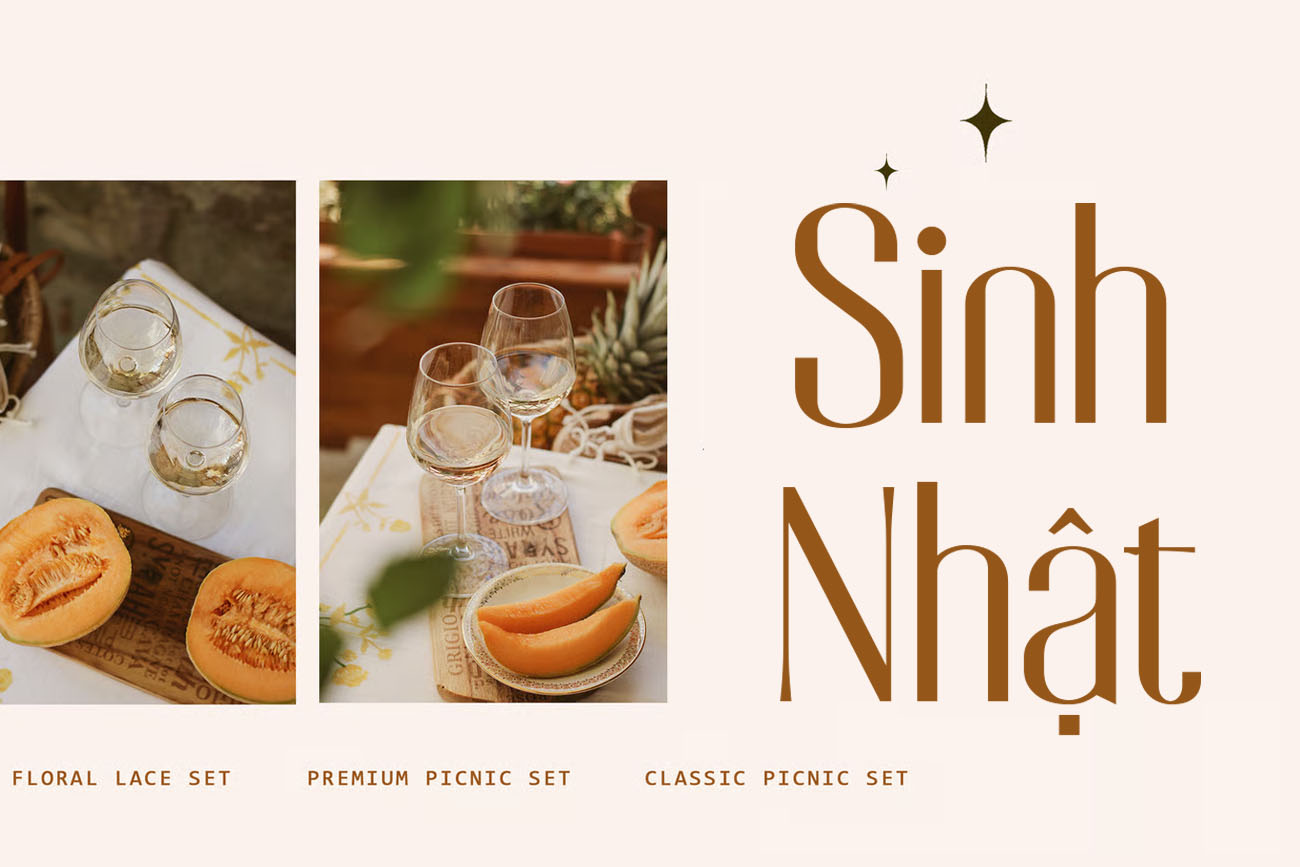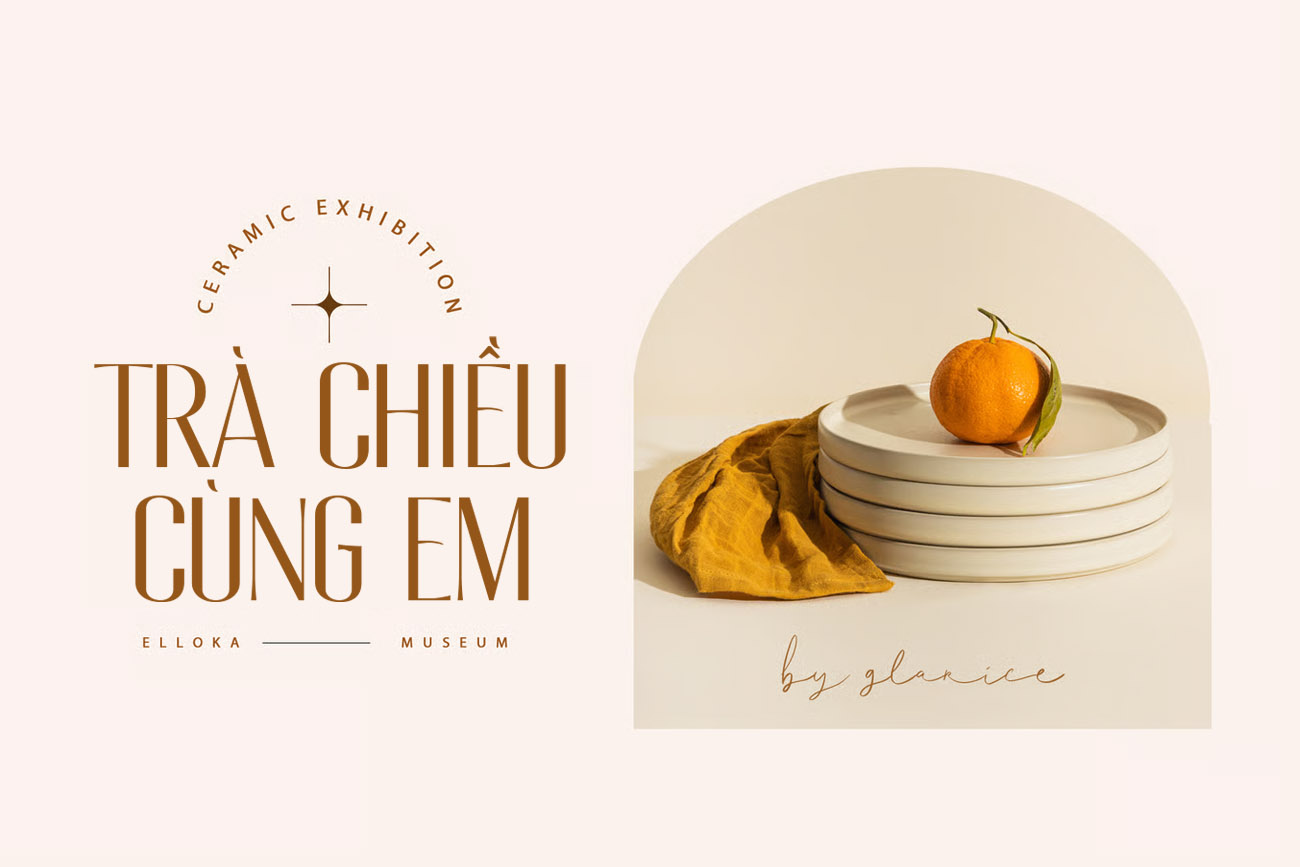
Font Chữ Việt Hóa Phong Cách Condensed Hiện Đại TH Belly & Park
Trong thế giới thiết kế đồ họa, việc tìm kiếm một font chữ hiện đại nhưng vẫn giữ được nét thanh lịch và sang trọng luôn là bài toán khó đối với các designer. Để đáp ứng nhu cầu này, hôm nay chúng tôi xin giới thiệu đến cộng đồng sáng tạo bộ phông chữ TH Belly & Park, một tác phẩm ấn tượng được Việt hóa hoàn chỉnh, sẵn sàng nâng tầm mọi dự án thiết kế của bạn.
Sự giao thoa tinh tế trong thiết kế gốc
Belly & Park, tác phẩm gốc của nhà thiết kế tài năng Yipianesia, là một bộ typeface thuộc dòng Sans Serif với phong cách Condensed (thu hẹp bề ngang). Ngay từ cái nhìn đầu tiên, bộ phông này đã chinh phục người xem bởi vẻ đẹp "Beauty Classic" – một sự kết hợp hoàn hảo giữa cấu trúc hình học hiện đại và những đường nét mềm mại, hoài cổ.
Điểm đặc biệt của Belly & Park nằm ở sự tương phản nhẹ nhàng giữa các nét, tạo nên cảm giác cao ráo, thanh thoát nhưng vô cùng vững chãi. Đây là lựa chọn lý tưởng cho những ai đang tìm kiếm sự tối giản nhưng không hề đơn điệu.
Phiên bản Việt hóa hoàn hảo từ Team TH
Hiểu được giá trị thẩm mỹ của bộ phông này cũng như nhu cầu sử dụng tiếng Việt trong các thiết kế chuyên nghiệp, Team TH đã tiến hành thực hiện phiên bản font chữ Việt hóa mang tên TH Belly & Park.
Không chỉ đơn thuần là thêm dấu, Team TH đã dành nhiều tâm huyết để tinh chỉnh lại kerning (khoảng cách giữa các ký tự) và vị trí của các dấu câu sao cho hài hòa nhất với cấu trúc Condensed đặc trưng của font gốc. Nhờ đó, các đoạn văn bản tiếng Việt khi hiển thị vẫn giữ được "linh hồn" và sự mượt mà vốn có của bản gốc, giúp các designer không còn lo lắng về lỗi hiển thị hay sự mất cân đối khi gõ tiếng Việt.
Ứng dụng đa dạng trong thiết kế
TH Belly & Park là một font chữ hiện đại cực kỳ linh hoạt. Với vẻ ngoài sang trọng, nó đặc biệt phù hợp cho các dự án:
• Thiết kế Logo & Branding: Tạo nên diện mạo thương hiệu đẳng cấp, đặc biệt là trong các ngành thời trang, mỹ phẩm và trang sức.
•  Editorial Design: Sử dụng làm tiêu đề cho tạp chí, poster phim hoặc bìa sách cần sự thu hút mạnh về thị giác.
• Bao bì sản phẩm: Tăng tính thẩm mỹ và giá trị cho sản phẩm nhờ typography tinh tế.